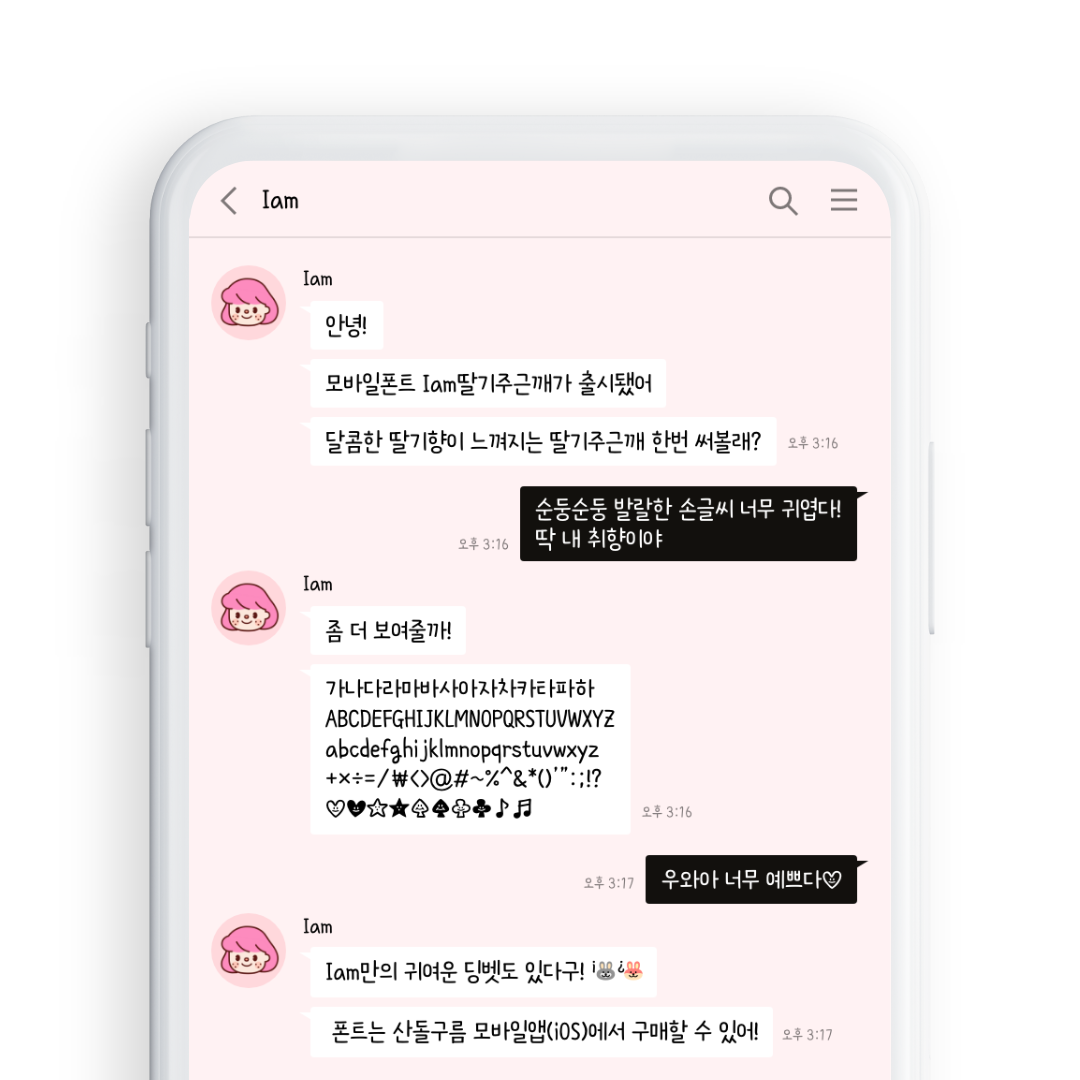
Iam 딸기주근깨
Iam
Iam 딸기주근깨 font in use
Iam 딸기주근깨는 모바일 전용으로 제작된 폰트입니다.
코끝에 느껴지는 달콤한 딸기향과 귀여운 주근깨! 딸기주근깨는 순둥순둥하면서 발랄함을 가진 친구에요.
순해서 마음이 편안해지는 딸기주근깨를 만나보세요!
Iam 딸기주근깨에는 귀여운 딩벳이 숨어있어요. 키패드에서 물음표와 느낌표를 꾹 눌러서 ¿ 역물음표와 ¡ 역느낌표를 타이핑 해보세요!
• Iam 딸기주근깨 / Iam Berryfreckle